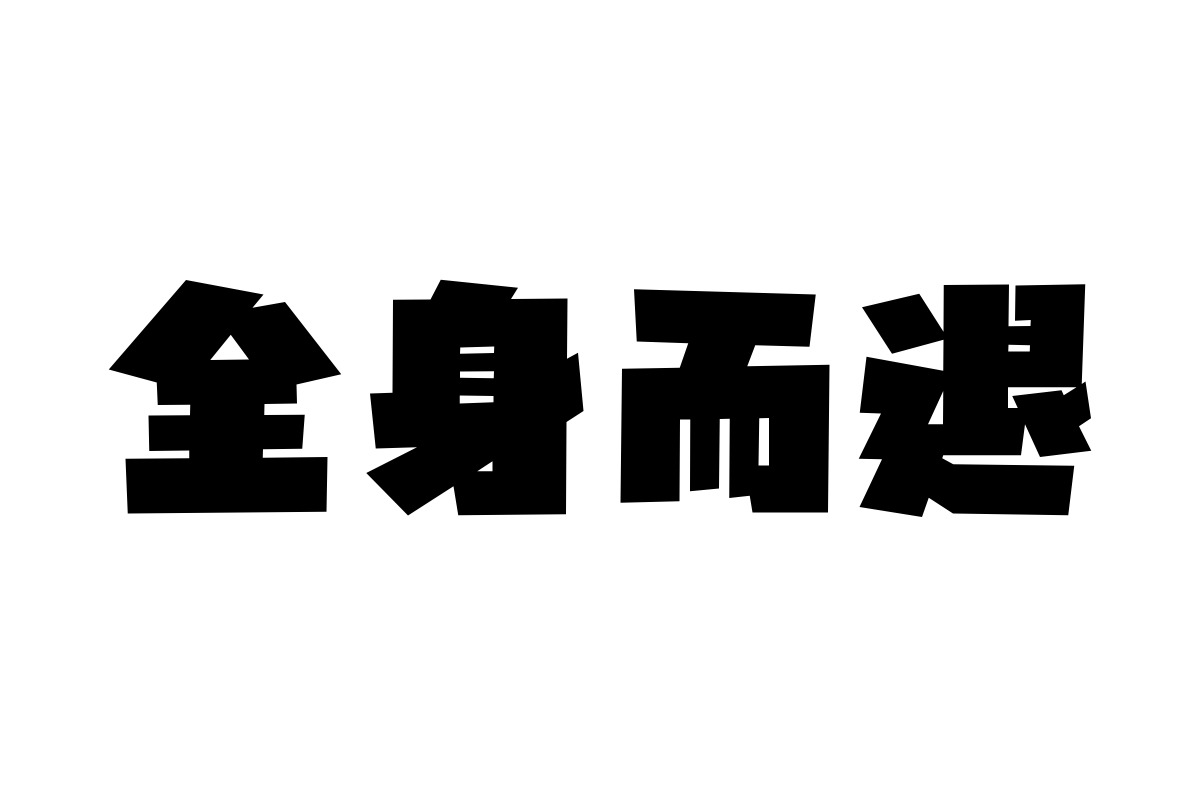
汉仪铸字多米诺是一款现代简约风格的中文字体,由汉仪公司设计。这款字体具有独特的笔画和字形结构,给人一种简洁、大气的感觉。它的笔画流畅,线条清晰,适合用于各种印刷品和数字媒体。
汉仪铸字多米诺的特点如下:
1. 简洁大方:这款字体的线条简单明了,没有过多的装饰,给人一种简洁、大方的感觉。
2. 易于识别:由于其独特的笔画和字形结构,使得这款字体在众多字体中脱颖而出,易于识别。
3. 适应性强:无论是用于印刷品还是数字媒体,汉仪铸字多米诺都能展现出其独特的魅力。
总之,汉仪铸字多米诺是一款非常实用的中文字体,无论是用于印刷品还是数字媒体,都能展现出其独特的魅力。